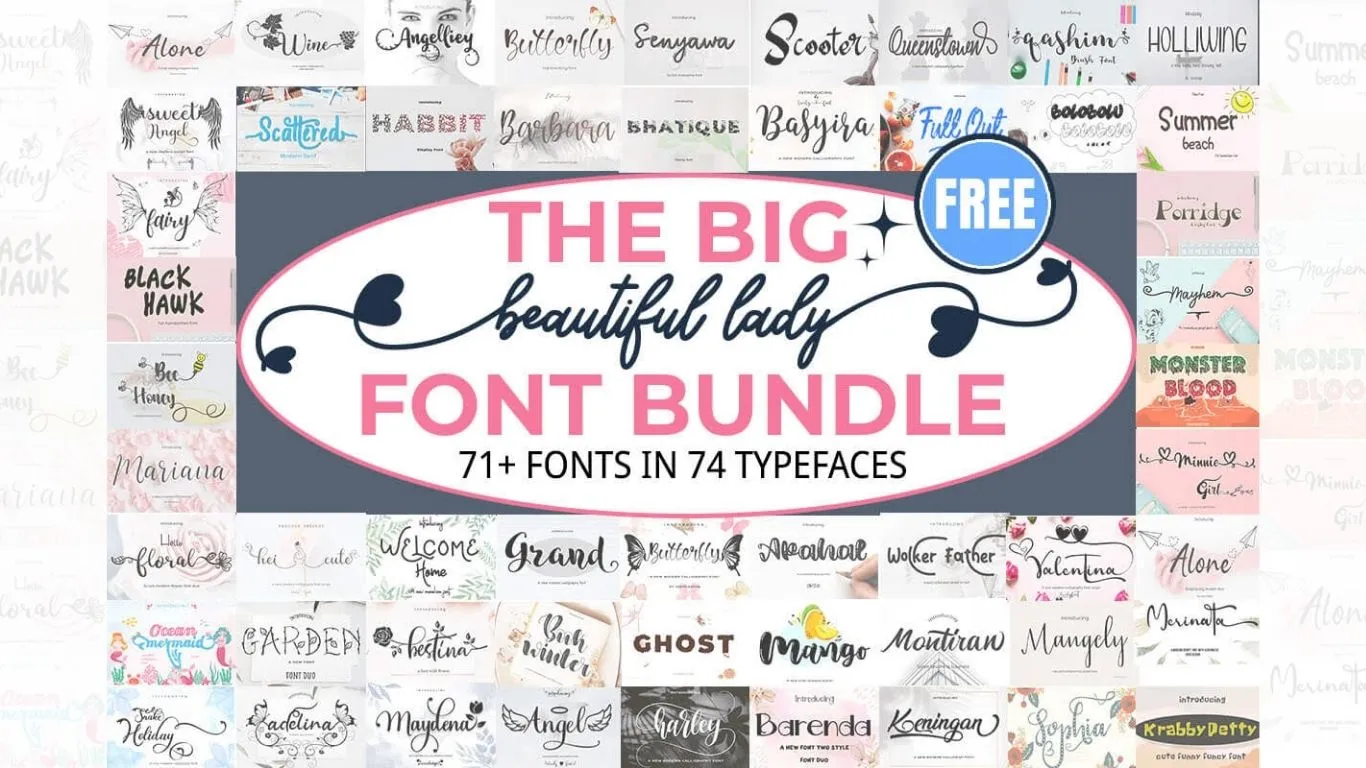
Creative Fabrica 免費字體包 The Beautiful Lady Font Big Bundle
字體包裡有什麼?
The Beautiful Lady Font Big Bundle 由 cocodesign 工作室出品,整套共收錄 71+ 款字體,分布在 74 個字型檔案中,風格多元,幾乎涵蓋你在設計工作中可能會用到的所有手寫與展示字型類別。
以下列舉部分收錄字體:
手寫草書 (Script & Handwritten):Angel、Pomade、Bee Honey、Valentina、Ocean Mermaid、Sweet Angel、Dream Boho、Sophia、Mariana、Book Winter、Garden、Gardiner 等數十款。
展示字型 (Display):Graffiti Stroke、Monster Blood、Megatron、Ghost、Apahal、Arjudah、Krabby Petty 等。
襯線與無襯線 (Serif / Sans-Serif):Akoya、Wolker Father、Rumpia 等。
裝飾與特殊風格:Fairy、Hello Floral、Butterfly、Milk Sheep、Snake Holiday 等。
這些字體整體偏向女性化、優雅唯美的設計方向,適合需要精緻感的設計專案。